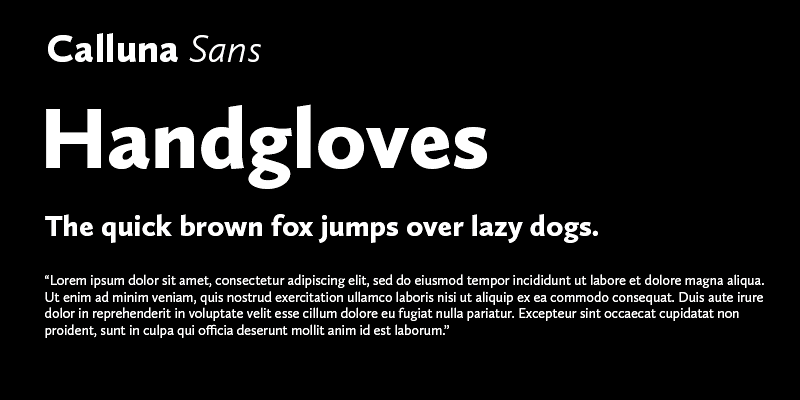
Calluna Sans ist eine charaktervolle, humanistische Sans, die auf der beliebten Schriftfamilie Calluna basiert. Genau wie Calluna verfügt sie über echte Kursivschrift, Kapitälchen, viele Ligaturen, 4 Ziffernsätze und vieles mehr. Calluna Sans gibt es in 5 Schnitten mit jeweils einer Kursivschrift.
Jos Buivenga lebt und arbeitet in Arnhem. Er begann seine Laufbahn als Schriftdesigner im Jahr 1994 und gründete zehn Jahre später den Schriftenhersteller exljbris. Er ist vor allem für seine Schriftfamilie Museo bekannt und für die Art, wie er seine Schriften vermarktet.